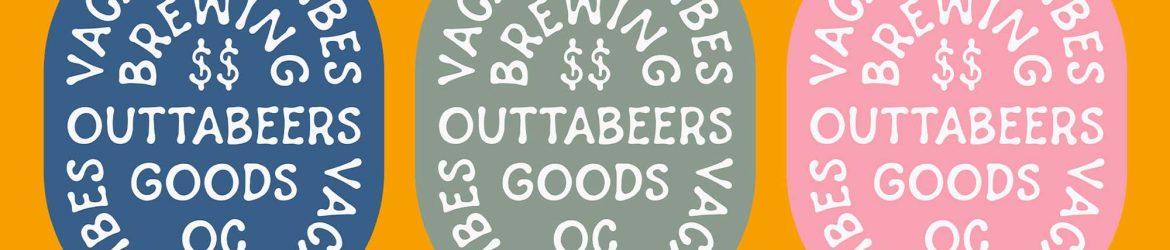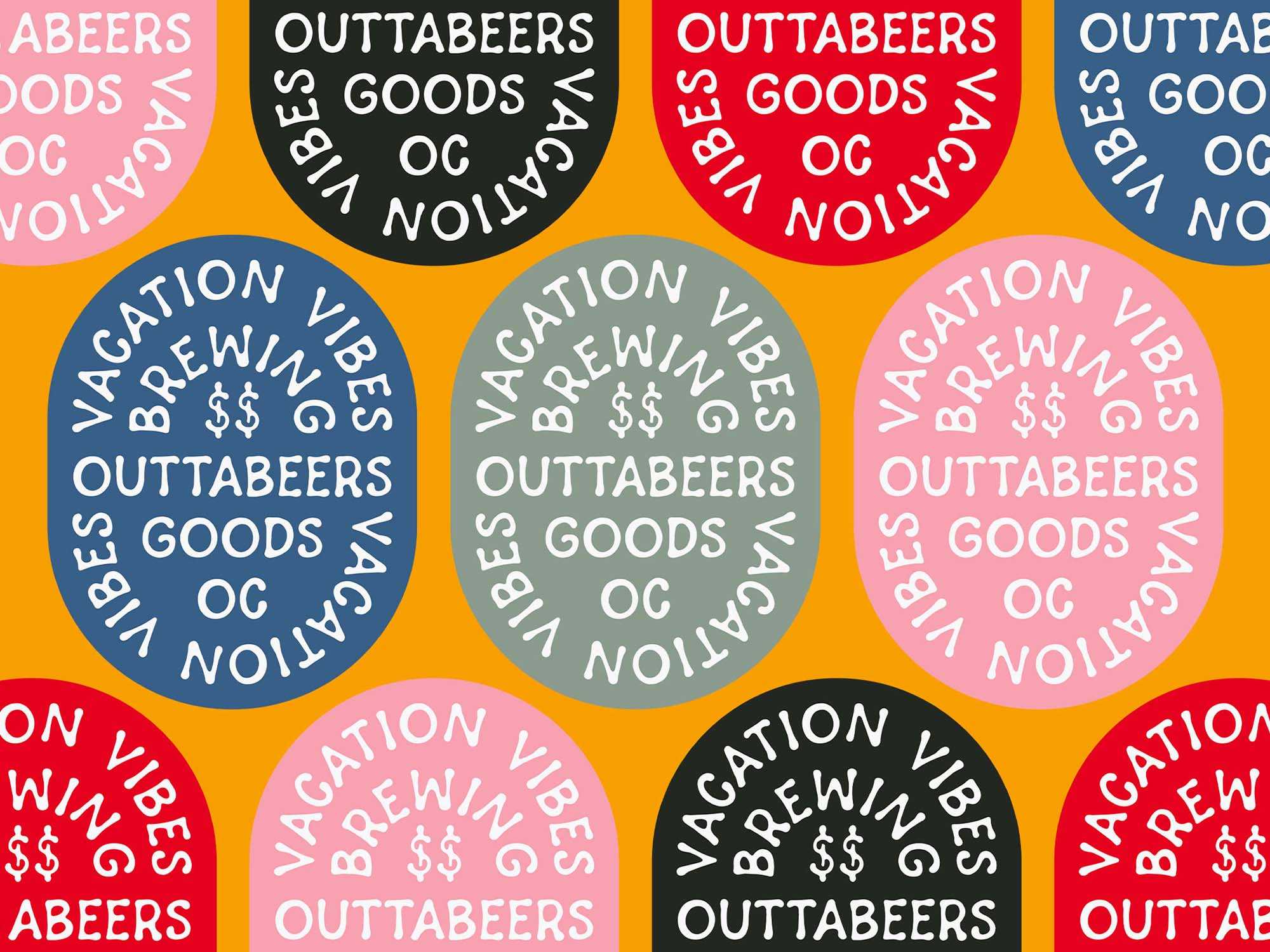
Vacation Vibes Font
Descubra o verdadeiro significado da frase “vai embora daqui”, especialmente em tempos atuais. Não há período ou lugar certo para relaxar e cuidar de si mesmo. Quando a saúde mental e física o pede, uma pausa pode ser a melhor solução. Este recurso gráfico é a solução perfeita para aqueles dias em que você está procurando aquele impulso para dar um passo. Este é o Vacation Vibes, uma fonte que reflete o encanto de uma pausa, com suas curvas suaves e terminações robustas. Este é o par perfeito para criar um design inigualável. Sinta-se à vontade para explorar, experimentar e personalizar este design único. Sua pausa merece um tom vibrante e animado.